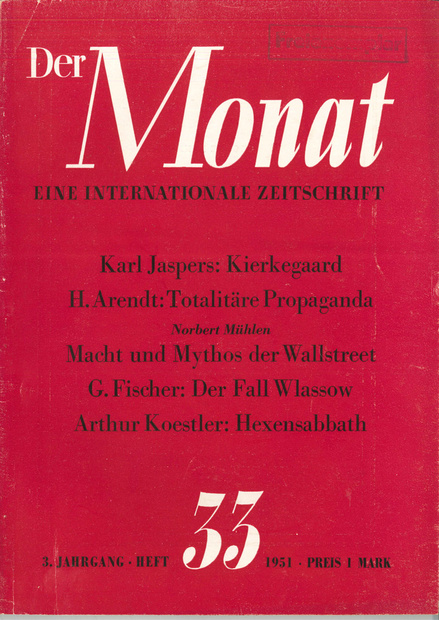
Suche Schriftart der Zeitschrift "Der Monat" aus den 1950er Jahren
ich suche die Schriftart/en des Titelblatts der oben gezeigten Zeitschrift.
Das ist größtenteils aus einer Bodoni gesetzt. Der Titel allerdings nicht, möglicherweise ist der ja gezeichnet. :-?
Fürchte eher, da hat sich eine® an der (bzw. einer) Bodoni vergangen.